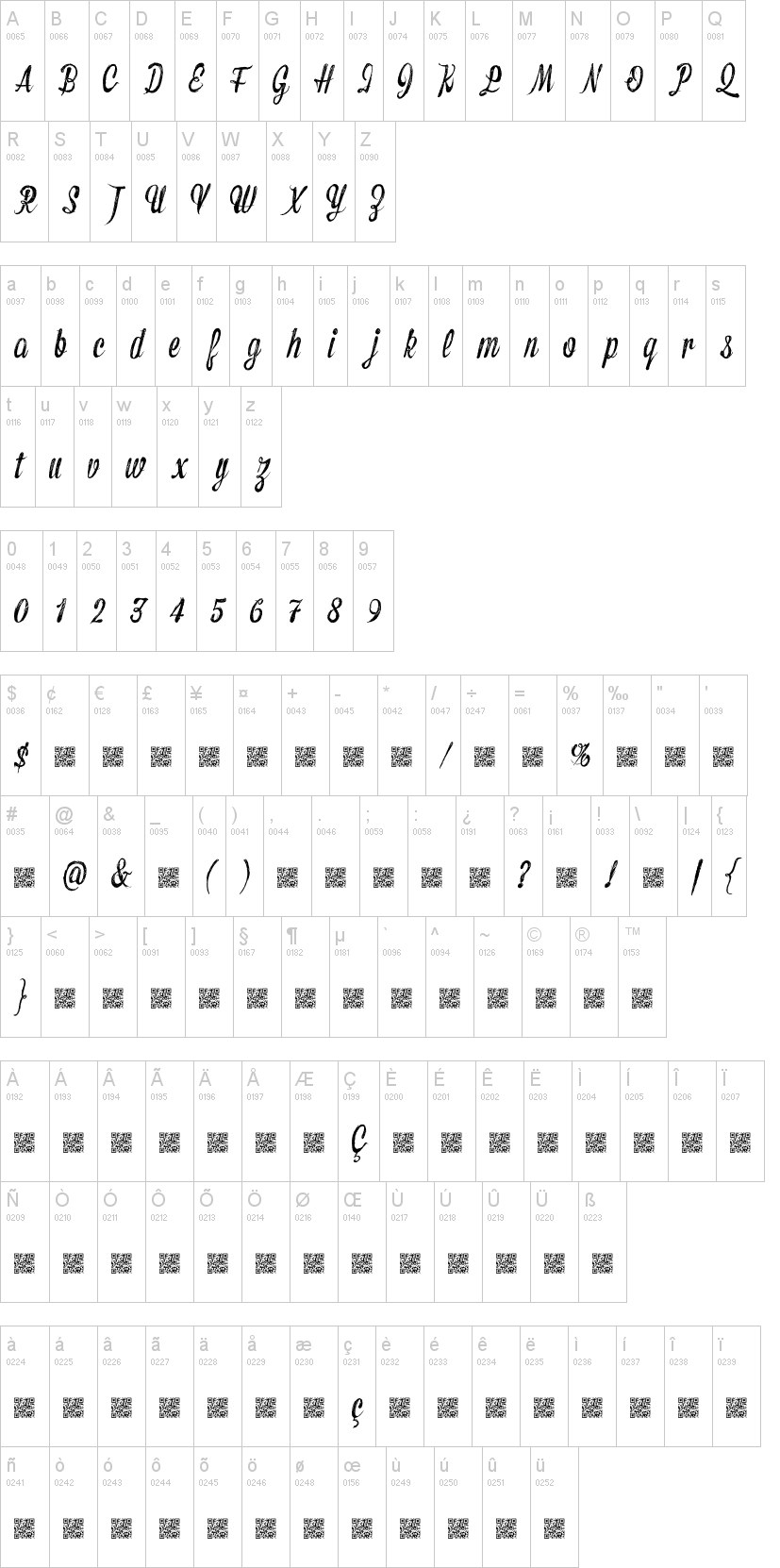
Tragic Prequel
? Tragic Prequel 字体是一款由 Typodermic Fonts 公司推出的英文字体,它拥有一种放大招牌的复古风格,让字体看起来更加粗犷而优雅。它的特点是字体的边缘细腻,字母间距也比较大,使得字体更加易读。它的字重也很轻,使得字体更加精致,具有细腻的质感。它的字形也比较特别,可以满足不同的设计需求,适用于不同的平台,是一款很好的复古风格字体。
Tragic Prequel是一款非常不错的手写艺术字体,具有很好的视觉感,适合于文化类的宣传设计、商业类品牌的广告和产品包装设计以及个性化文字排版等较多场景。
Tragic Prequel字符映射图